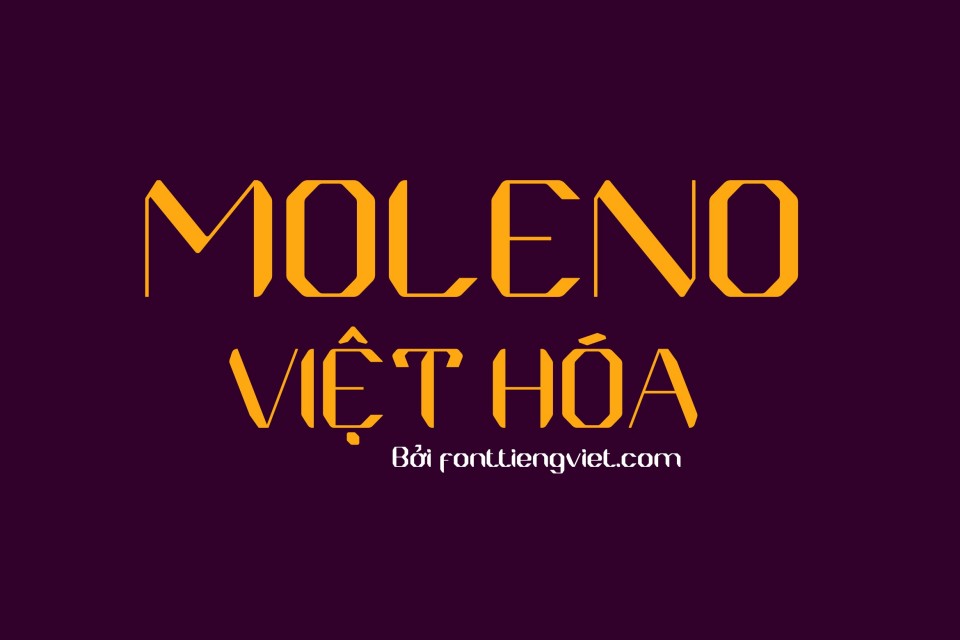
Font việt hóa 1FTV Moleno
Trong thế giới đồ họa hiện đại, việc lựa chọn một bộ Font Miễn Phí chất lượng là yếu tố then chốt để tạo nên sự khác biệt. Font việt hóa 1FTV Moleno nổi lên như một lựa chọn hoàn hảo nhờ sự kết hợp giữa nét cổ điển tinh tế và hơi thở đương đại. Đây là bộ font được cộng đồng thiết kế tại Việt Nam đánh giá cao bởi khả năng ứng dụng linh hoạt trong nhiều loại hình sản phẩm khác nhau. Với sự chăm chút kỹ lưỡng trong quá trình việt hóa, bộ font này đảm bảo hiển thị đầy đủ các dấu tiếng Việt mà không gặp lỗi kỹ thuật, giúp người dùng tự tin hơn trong quá trình sáng tạo.
Đặc điểm nổi bật của Font việt hóa 1FTV Moleno
Kiểu dáng và tính ứng dụng thực tế
Font việt hóa 1FTV Moleno mang trong mình những đường nét thanh mảnh nhưng vô cùng chắc chắn. Cấu trúc chữ được thiết kế cân đối, tạo cảm giác dễ chịu cho người xem ngay từ cái nhìn đầu tiên. Đối với các bạn học sinh và giáo viên, bộ font này rất phù hợp để trình bày các bài thuyết trình, làm thiệp chúc mừng hoặc trang trí báo tường. Sự rõ ràng của các ký tự giúp nội dung văn bản trở nên chuyên nghiệp và dễ tiếp nhận hơn bao giờ hết.
Tối ưu hóa cho người dùng Việt Nam
Điểm mạnh nhất của phiên bản này chính là việc xử lý các dấu thanh và ký tự đặc biệt một cách mượt mà. Bạn sẽ không còn lo lắng về tình trạng các dấu bị lệch hay font bị nhảy khi gõ tiếng Việt trên các phần mềm như Photoshop hay Word. Điều này giúp tiết kiệm thời gian chỉnh sửa và nâng cao hiệu suất làm việc cho các nhà thiết kế không chuyên.